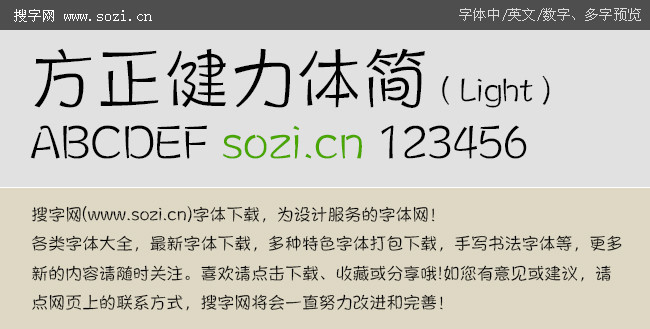
方正健力體簡Light
搜字網(wǎng)提供一款方正健力體簡中文字體下載,方正健力體是作者從某健身的標(biāo)志引發(fā)的靈感,點(diǎn),撇,捺,抅,橫,直劃等都是不同方向,也好像各種健身項(xiàng)目的不同表達(dá)方式一樣,是一款充滿動(dòng)感和活力的字體。適合健美行業(yè),活力飲料,運(yùn)動(dòng)服裝和運(yùn)動(dòng)鞋的廣告宣傳。